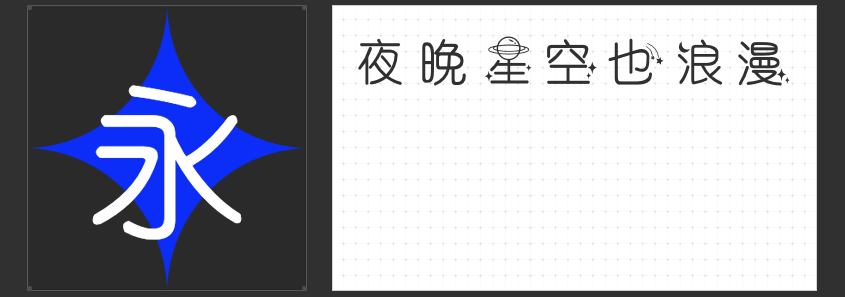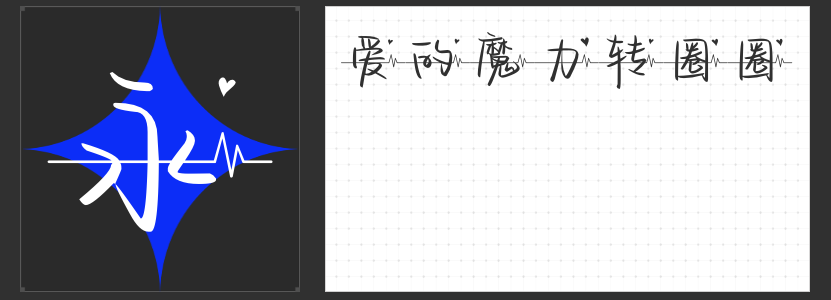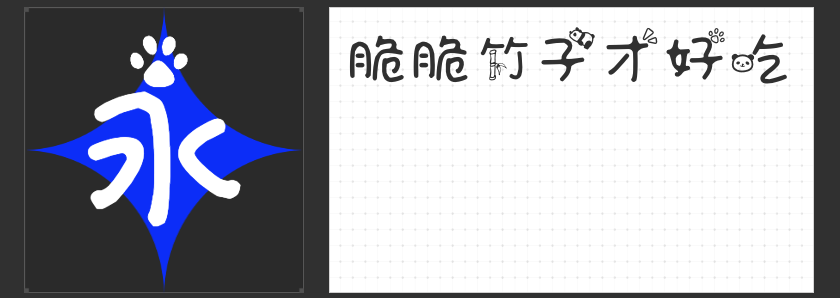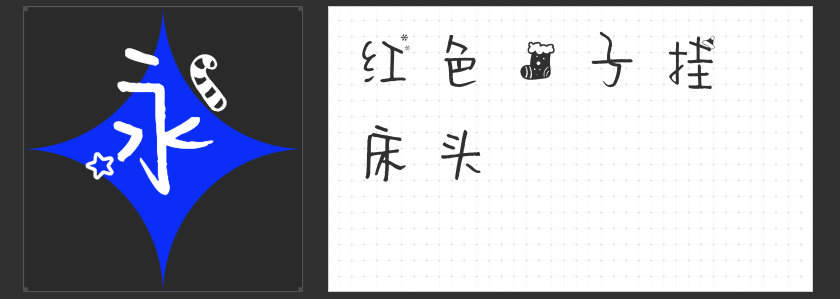
萌动心扉:四款超可爱设计字体点亮创意灵感
在这个个性化表达的时代,字体不仅仅是文字的载体,更是情感和创意的延伸。今天,我们要向大家推荐四款极具特色的超可爱设计字体。这些字体以其独特的设计元素,为日常的文字交流增添了无尽的乐趣与想象空间,无论是用于社交媒体的签名档、贺卡的设计,还是儿童读物的插图,都是不可多得的选择。
1. 字圈也字小熊猫
“字圈也字小熊猫”字体巧妙地将国宝大熊猫的形象融入汉字之中,如“竹”字的竖笔画被替换成了可爱的竹子形状简笔画,而“熊”字则添加了憨态可掬的小熊猫图案,还有一些字上点缀着小熊猫的爪印。这款字体不仅适合用于儿童图书的设计,也能为各种宣传海报增添一份萌趣。试想一下,在一张邀请函上看到这样可爱的字体,怎能不让人眼前一亮?
2. 字圈也字星河浪漫体
“字圈也字星河浪漫体”将浩瀚星空的元素巧妙地融入到每一个字符之中,其中最具特色的是“字”宝盖头上的点笔画被替换成了闪闪发光的星星。此外,该字体还在其他字里加入了星座、行星等天体图案作为装饰,仿佛带领读者踏上了一场穿越宇宙的浪漫之旅。使用这款字体编写的文字,无论是在情人节的贺卡上,还是在星空主题的派对邀请函中,都能营造出一种神秘而又浪漫的氛围。
3. 字圈也字圣诞快乐
“字圈也字圣诞快乐”是一款充满节日气氛的手写字体,设计师在字体中巧妙地加入了圣诞树、铃铛、礼物盒等节日元素,尤其值得一提的是,“袜”字被设计成了一个袜子的简笔画形象,充满了童真与趣味。这款字体非常适合用于圣诞节相关的活动宣传或装饰,它能让每一个看到的人都感受到浓浓的节日喜悦。
4. 字圈也字爱的心电图
“字圈也字爱的心电图”则是以心电图为设计灵感,每个字符都被赋予了心跳的波形,当这些字符连成句子时,便构成了一幅连续的心电图,仿佛在诉说着爱的故事。无论是制作情侣间传达感情的信件,还是朋友间表达情谊的手工卡片,这款字体都能完美地传递出那份温暖与关怀。
这四款超可爱设计字体以其独特的创意和丰富的视觉效果,为我们的日常生活带来了无限的可能。它们不仅是文字的呈现形式,更是一种情感的表达方式。希望这些推荐能够激发你的创意灵感,让你在接下来的设计工作中大放异彩。无论是为了个人使用,还是商业项目,这些字体都将是你不可或缺的好伙伴。